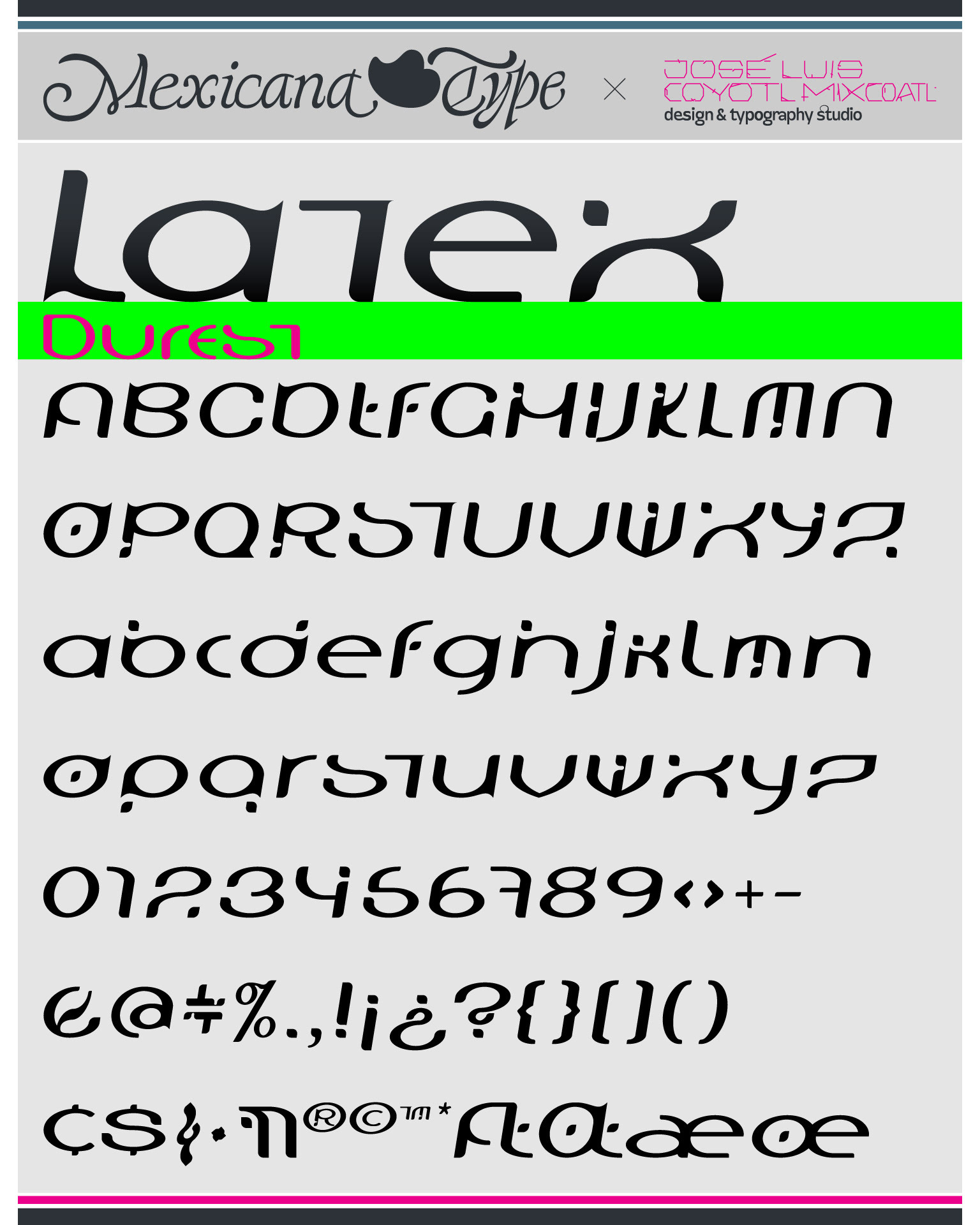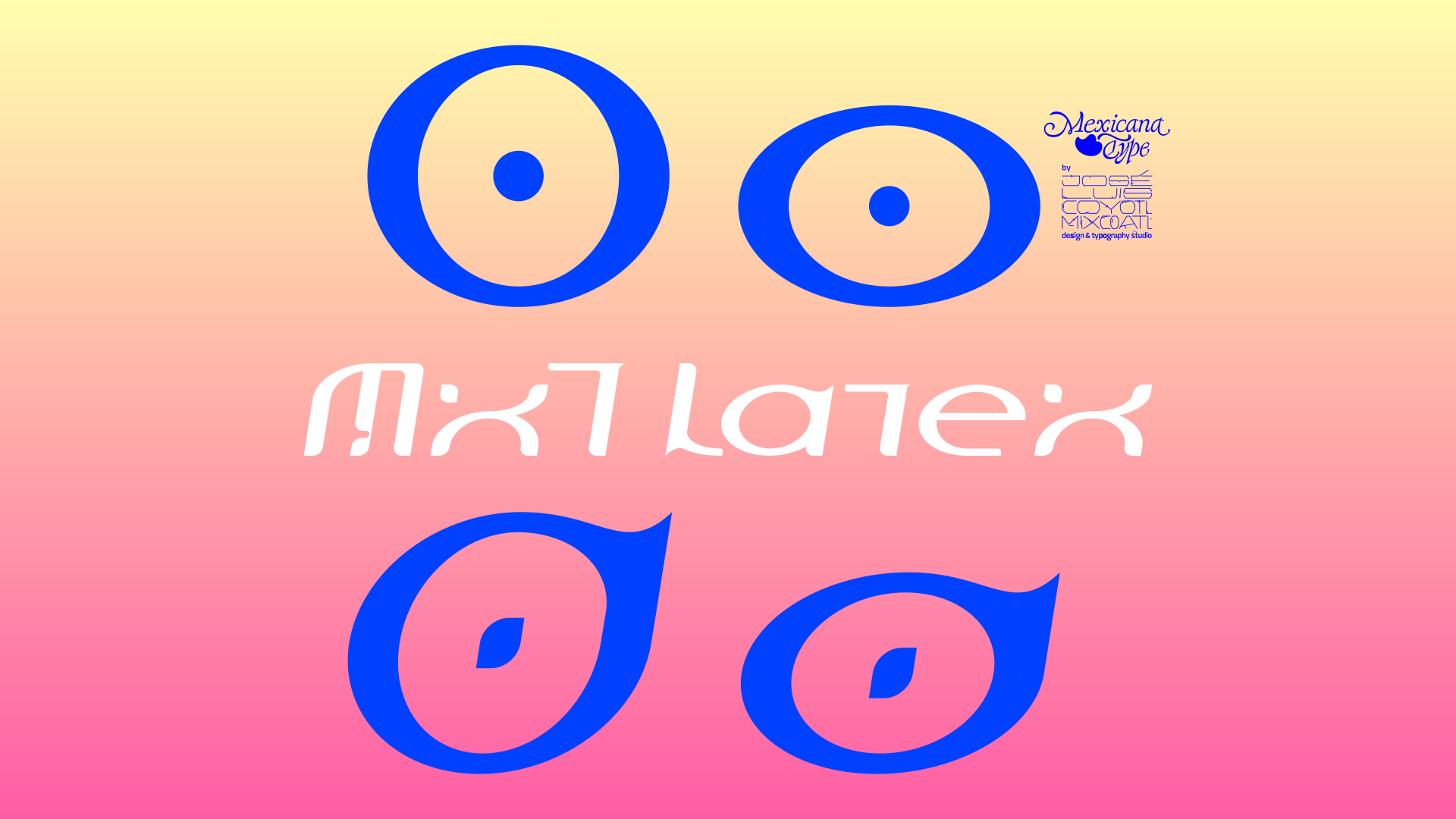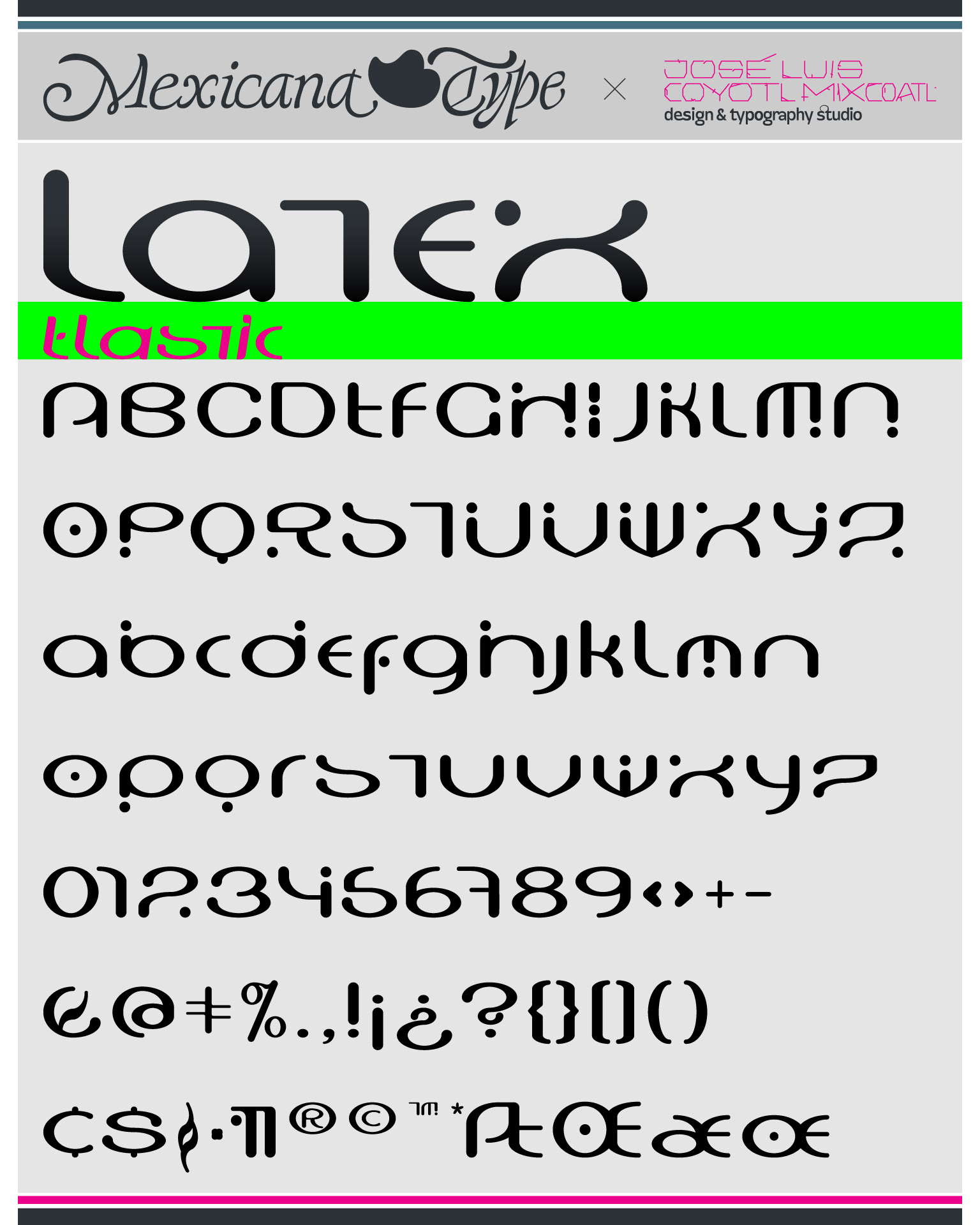
El desarrollo de MxT Latex en su momento, a inicios de los 2000, explora una combinación entre lo experimental, lo techno y lo orgánico. Su base estructural en el cuerpo de la letra es completamente modular, en las que curvas y rectas del cuerpo de cada letra, asi como detalles y terminaciones a manera de remates visuales de algunos de sus trazos, en conjunto con la anchura de su cuerpo y las proporciones de sus alturas en altas y bajas, así como en sus ascendentes y descendentes, la definen y le dan una personalidad muy particular, haciéndola compleja y simple a la vez. Es una tipografía rica en textura tipográfica en textos cortos y medianos e interesante como cuerpo de texto, cualquiera que sea su aplicación, siempre dará un display atractivo y expresivo.